输入一个名字,挑一个样式,下载 PNG。就这么简单,大约十秒钟。
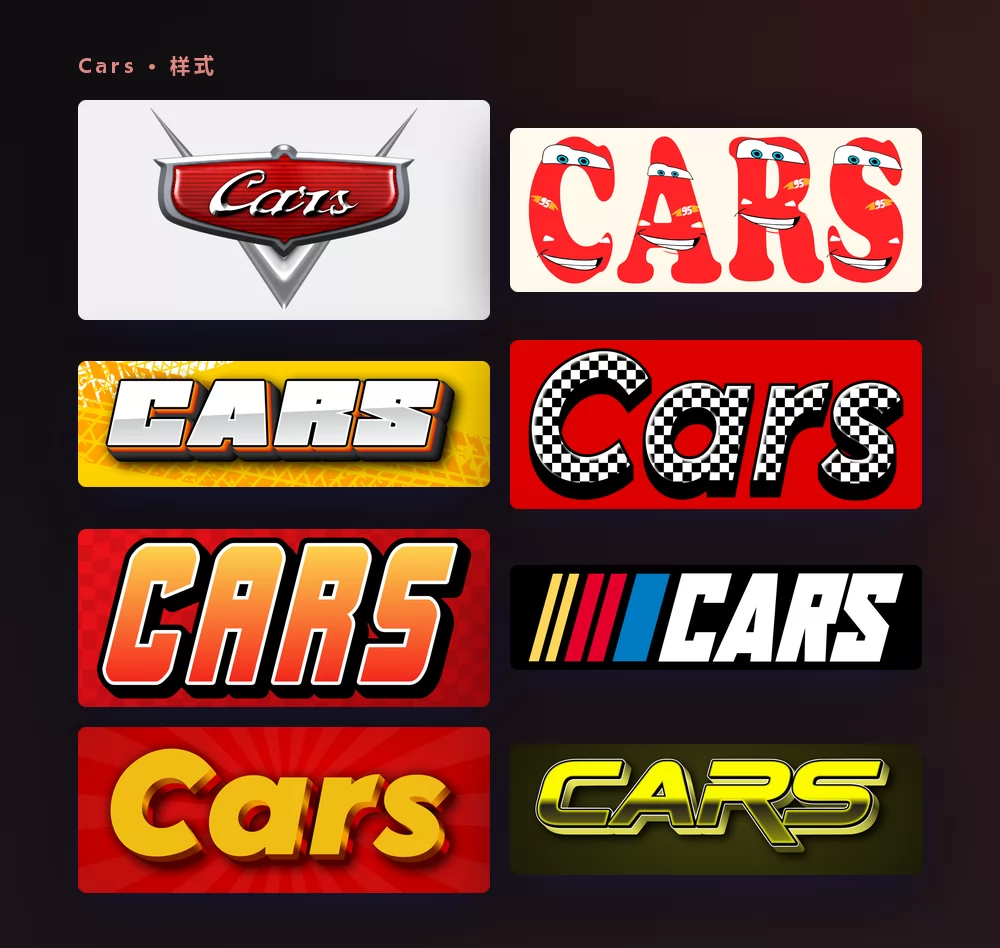
关于汽车总动员的字体
《汽车总动员》是皮克斯 2006 年的电影,讲的是一个由汽车当主角的世界。它的片名不是打出来的,是搭出来的:一行镀铬字放进一枚盾形徽章里,更像拧在五十年代轿车引擎盖上的装饰,而不是电影海报。
字形本身非常接近 Magneto Bold,由 Leslie Cabarga 设计,Font Bureau 于 1995 年发行。微软自家的字体页面这样描述它:让人想起「四五十年代冰箱门和汽车后备箱那些圆润曲面上的镀铬条字样」,正是这部电影所引用的年代。
怎样做汽车总动员风格文字
第一步:输入名字
打开生成器,把示例文字换成你自己的。徽章是围着这个词搭起来的,所以它就是为名字准备的:你一边打字,盾牌一边把自己填满。
第二步:挑一个样式
目标页面的样式就是徽章:镀铬字、红色烤漆、银色盾牌。列表里还有这部电影的整个赛车面,方格旗、轮胎印、赛车条纹,以及带着闪电麦坤眼睛的字母。「样式」选项卡里,两种都可以调整填充、描边和阴影。
第三步:选好尺寸
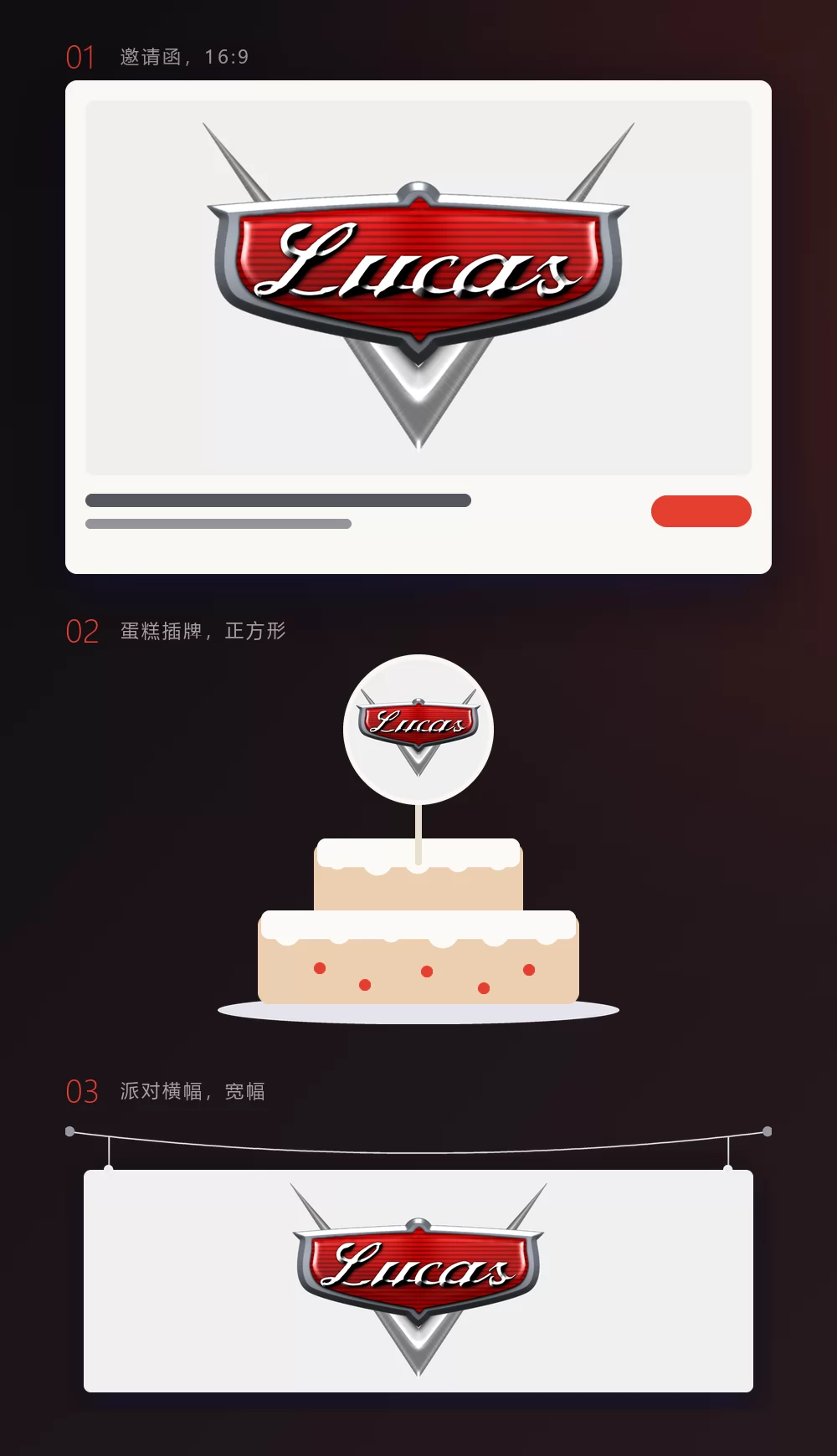
导出前先设好尺寸,之后就不用再裁。邀请函用 16:9,蛋糕插牌或头像用正方形,挂在桌子上方的横幅用宽条。上面三个情景模拟,就是这三种尺寸放到位之后的样子。
第四步:下载
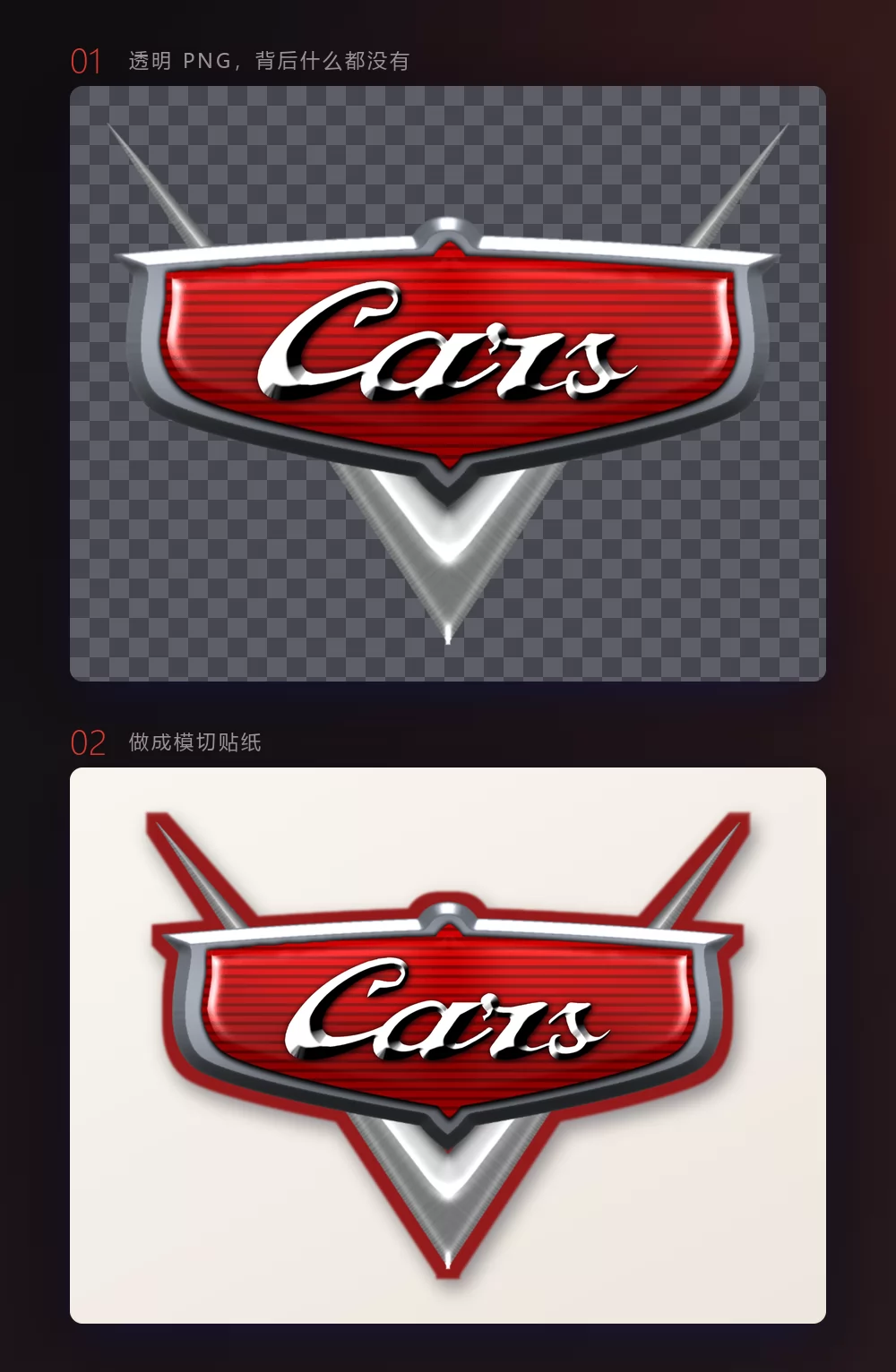
如果这枚徽章要放到别的东西上面,就在「下载」选项卡里选透明 PNG:你自己的照片、彩色卡纸、幻灯片、切割机。这是大多数人错过的选项,也是办派对时最要紧的一个,因为盾牌会保住自己的形状,而不是装在一个白色方框里过来。
徽章里装得下几个字母
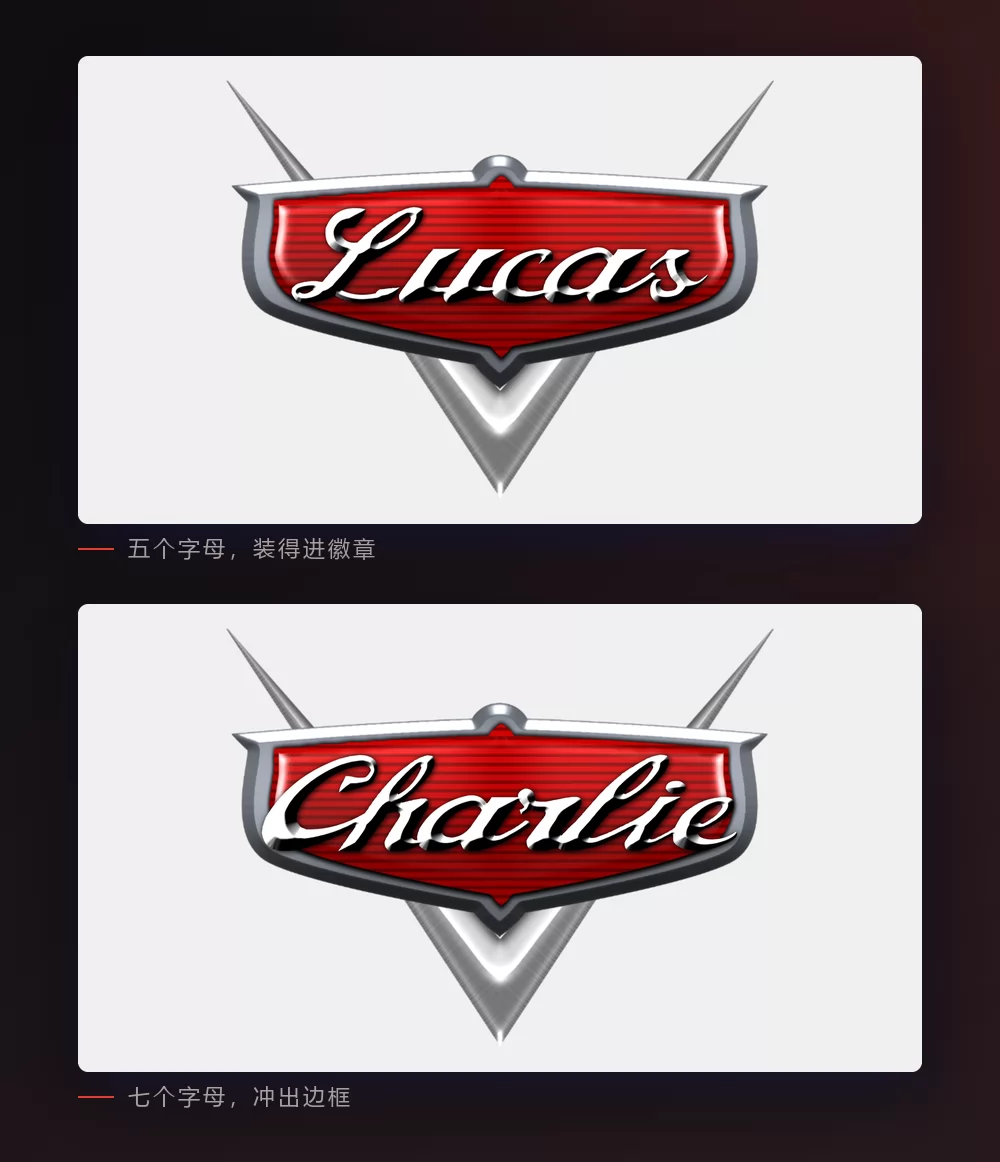
我们量过,因为这决定了你该选哪个样式。盾牌可以从容装下五个字母。到六个,第一个和最后一个就贴到银边了。到七个,它们已经在外面了,就像上面那样。
而且和其他所有样式不同,把文字改小并没有用:徽章会跟着词一起放大,比例始终不变。名字更长的话,答案不是某个设置,而是换一个样式。同一个列表里的赛车大写接受任何长度,它们没有可以冲出的框。
徽章的样子,还是麦坤字母的样子
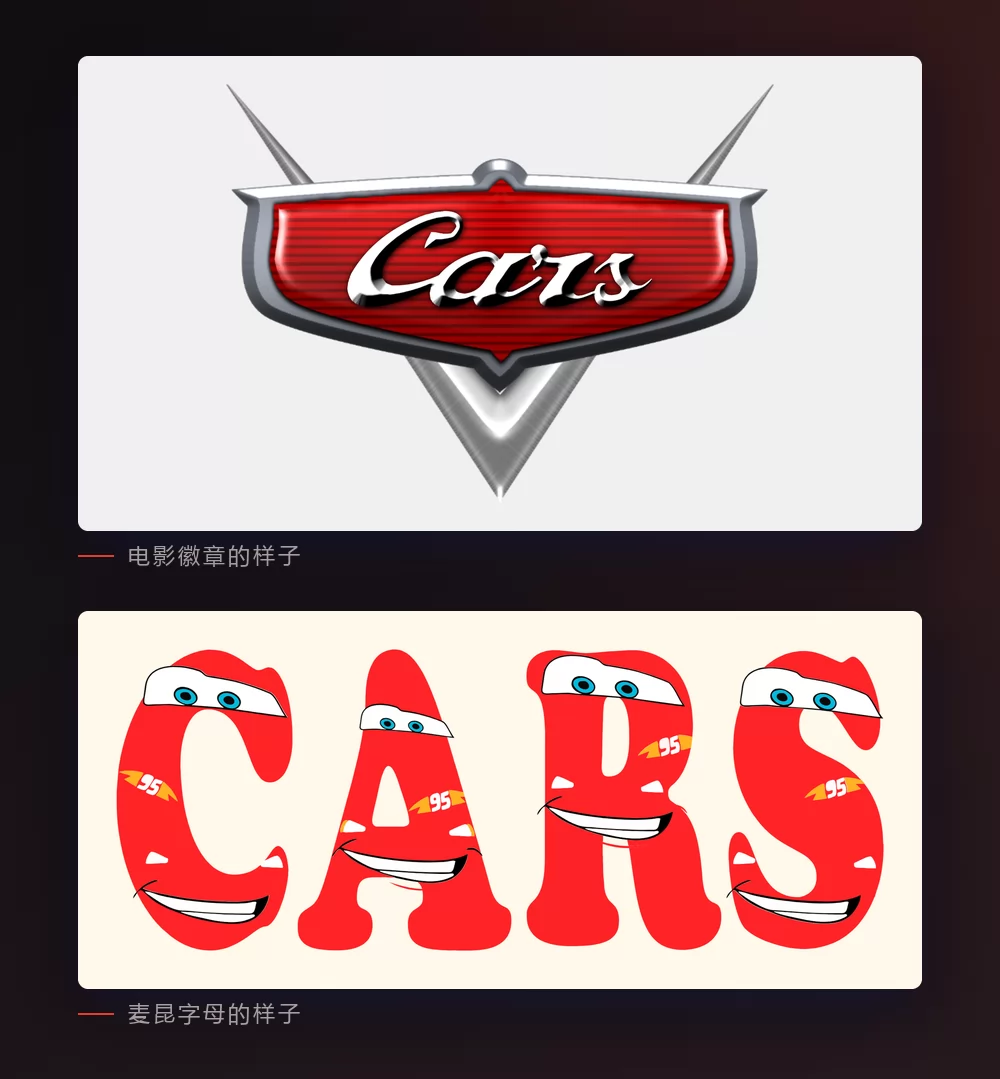
徽章就是这部电影的标志形状:银色盾牌里,红色烤漆上的镀铬字。人们说「汽车总动员的标志」时脑子里想的就是它,邀请函上的名字也该用它。
麦坤字母是大家搜索的另一半:每个字母都是一辆小红车,挡风玻璃处是眼睛,侧面是 95 的闪电标。它说的是那个角色而不是那部电影,做横幅比缩成头像更合适。
两种都在同一个列表里:你可以先用一种试一个名字,再换另一种,不用离开页面。
想安装字体的话,选哪一款
想要开放授权,老实的选择是 Google Fonts 上的 Alfa Slab One,由 JM Solé 于 2012 年设计,采用 SIL 开放字体授权。请清楚它给你什么、不给你什么:它是埃及体,带来的是粗细和笃定,而不是那道飘逸的笔锋。好几个别的生成器悄悄用的就是它。
这些字体都不会给你那枚盾牌。徽章是一个形状而不是一款字体,所以生成器才会围着你的文字把它画出来,而不是让你自己去找。
大家真正用它做什么
首先是生日派对,而且遥遥领先:邀请函、桌子上方的横幅、蛋糕插牌、卧室门上的名字、自制赛道上的号码。然后是教室门牌、小汽车视频的 YouTube 缩略图,偶尔还有为家庭聚会印的 T 恤。这些几乎都用透明 PNG 更好,因为大家认得的是盾牌和镀铬,而字体文件只给你字母的形状。
怎样在 Canva 里做汽车总动员风格文字
Canva 没有 Magneto,也没有这枚徽章。但它有 Alfa Slab One,所以不用离开 Canva 也能得到一个粗埃及体的标题,再从效果面板加上描边和阴影。至于徽章本身,就在这里做成透明 PNG 再上传:它能直接放进 Canva 的邀请函里,并保住形状。
Canva 的文字特效应用里有海量样式,但没有品牌标志这一类:Canva 不接受应用内出现第三方标志,所以这个效果还是得靠上传 PNG。
怎样在 Photoshop 里做汽车总动员风格文字
先看看字体菜单里有没有 Magneto。如果有,输入名字,然后用图层样式搭出镀铬效果:
- 渐变叠加放在字母上,浅灰到白再到中灰,竖直方向。镀铬是中间有一道硬转折的渐变,不是柔和过渡。
- 描边,位置外部,细一点,深灰色,让字母在红底上保住边缘。
- 投影又短又紧,然后在后面放一个圆角红色形状当烤漆面。
盾牌和它那两根银色尖角是画出来的形状。如果你要,从导出的 PNG 上描一遍会比从头搭快得多。
怎样在 Word 里做汽车总动员风格文字
Magneto 很可能已经在你的字体列表里了,这让 Word 在这里成了意外好用的选择。输入名字,设成 Magneto,然后用文本效果加描边和柔和阴影。你能得到字形,但得不到徽章,所以做邀请函还是在页面上放一张导出的 PNG 更好。
在手机上
常见问题
汽车总动员的标志用的是什么字体? 字形非常接近 Magneto Bold,由 Leslie Cabarga 为 Font Bureau 设计于 1995 年。外面那枚盾牌是画出来的形状,不属于任何字体。
怎样拿到空白的汽车总动员标志? 生成器就是这个:盾牌里放你自己的文字。输入名字然后下载,如果要放到别的东西上就选透明背景。
闪电麦坤的字体是什么? 大家指的是两件事之一:片名的字形,或者每个字母都是一辆带眼睛和闪电的小红车的那种样式。两种都在列表里。
为什么我的名字冲出了徽章? 盾牌大约装得下五个字母。到七个就会溢出,而且改小也没用,因为徽章会跟着一起变大。改用赛车样式吧,它们没有边框。
怎样做一条汽车总动员的生日横幅? 输入名字,选宽幅尺寸,下载透明 PNG,再印在你用的彩色纸上。